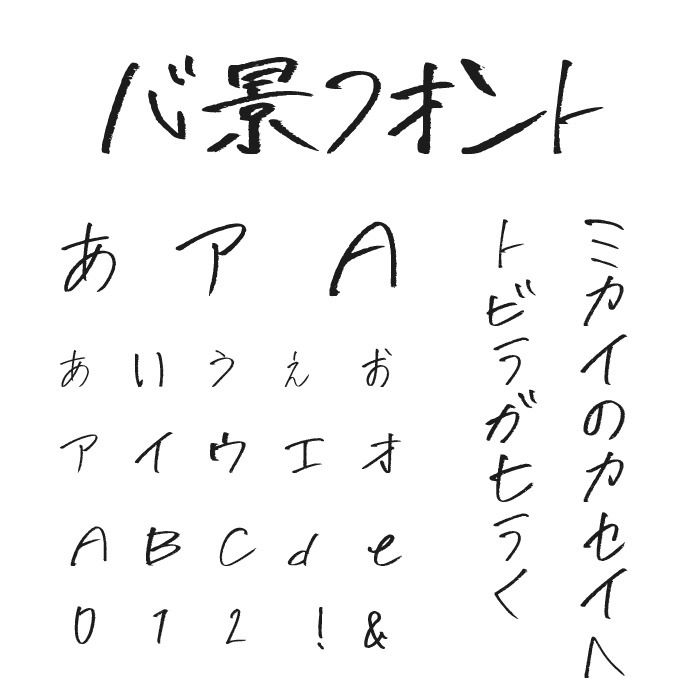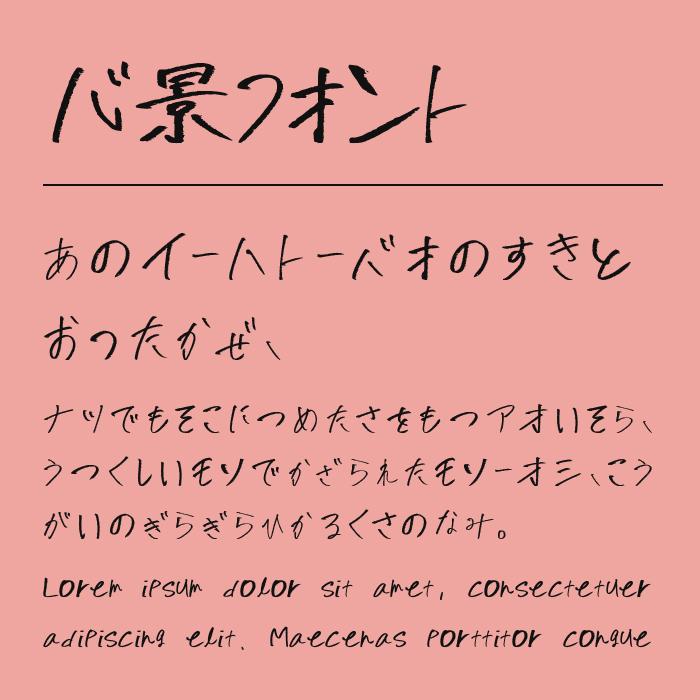
心景フォントは、心の中のつぶやきや感情の揺れをそのまま紙に書きつけたような、不安定さと繊細さが同居する手書き風フォントです。
文字によって線の太さや傾きが異なり、整いすぎないラフさが印象的で、感情の機微や余韻を伝える表現に向いているフォントです。。誰かの心象風景を綴ったような、どこか切なく、儚い印象を与える文字です。
和風テイストな書き文字で、静かに語りかける雰囲気を持っており、文学的なデザインやナレーション字幕、ZINEなどともぴったり。
収録文字は、漢字・ひらがな・カタカナ・アルファベット・数字・記号が収録。